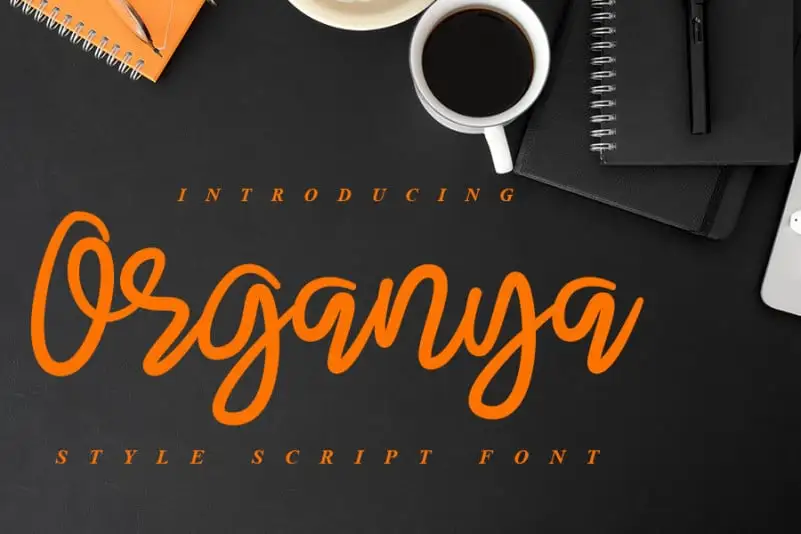
Organya Script Font – Download Grátis
A fonte Organya Script é uma elegante mistura entre influências clássicas do caligrafista e um toque contemporâneo e moderno. É perfeita para quem busca uma solução versátil para seus projetos, desde a criação de logotipos até a preparação das cartas pessoais ou o design de materiais de envio postal. A sua natureza sofisticada combina facilmente com qualquer estilo contemporâneo, proporcionando um resultado profissional e divertido ao mesmo tempo. Esta fonte é uma escolha perfeita para designers gráficos proativos que desejam incorporar um toque único em seus projetos de arte digital ou impressão.